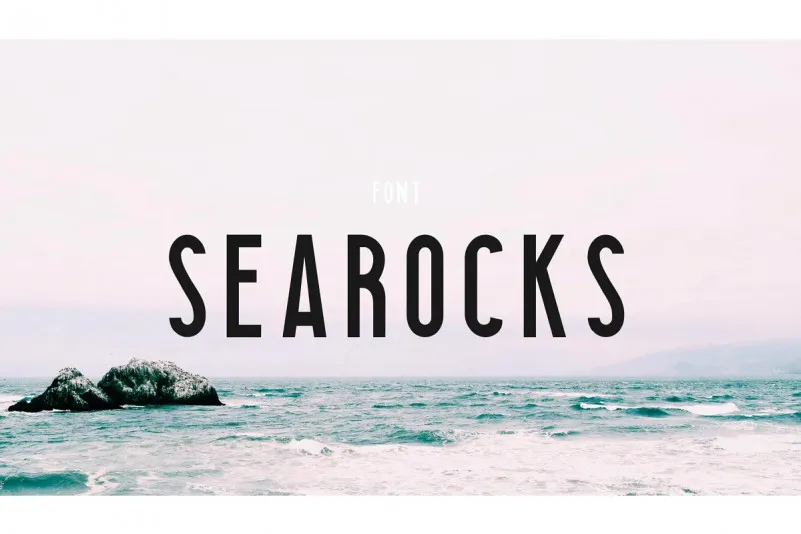
A Searocks Font é uma elegante e moderna tipografia sans serif que se destaca por sua simplicidade e clareza. Perfeita para aplicação em uma variedade de projetos, desde a criação de cartões postais encantadores até o desenvolvimento de logotipos vintage antigos. Com linhas leves e elegantes, essa fonte é um match perfeito para situações que exigem severidade no design. Ela se encaixa perfeitamente em ambientes que valorizam um estilo retro, especialmente quando combinada com outros tipos de fontes rústicas vintage e scripts antigos. Não importa o propósito ou o formato do seu projeto, a Searocks Font é uma escolha sólida para uma tipografia versátil.